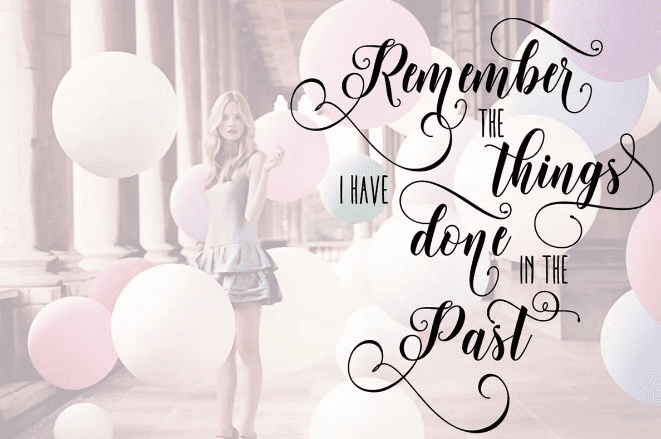
[Creativemarket] Metinoline Font
С более чем 640 глифами, Metinoline - это удивительно разнообразный и свежий шрифт для сценария, предоставляющий почти бесконечные возможности дизайна! С танцевальной основой и красивыми цветами, Metinoline определенно является полным пакетом.